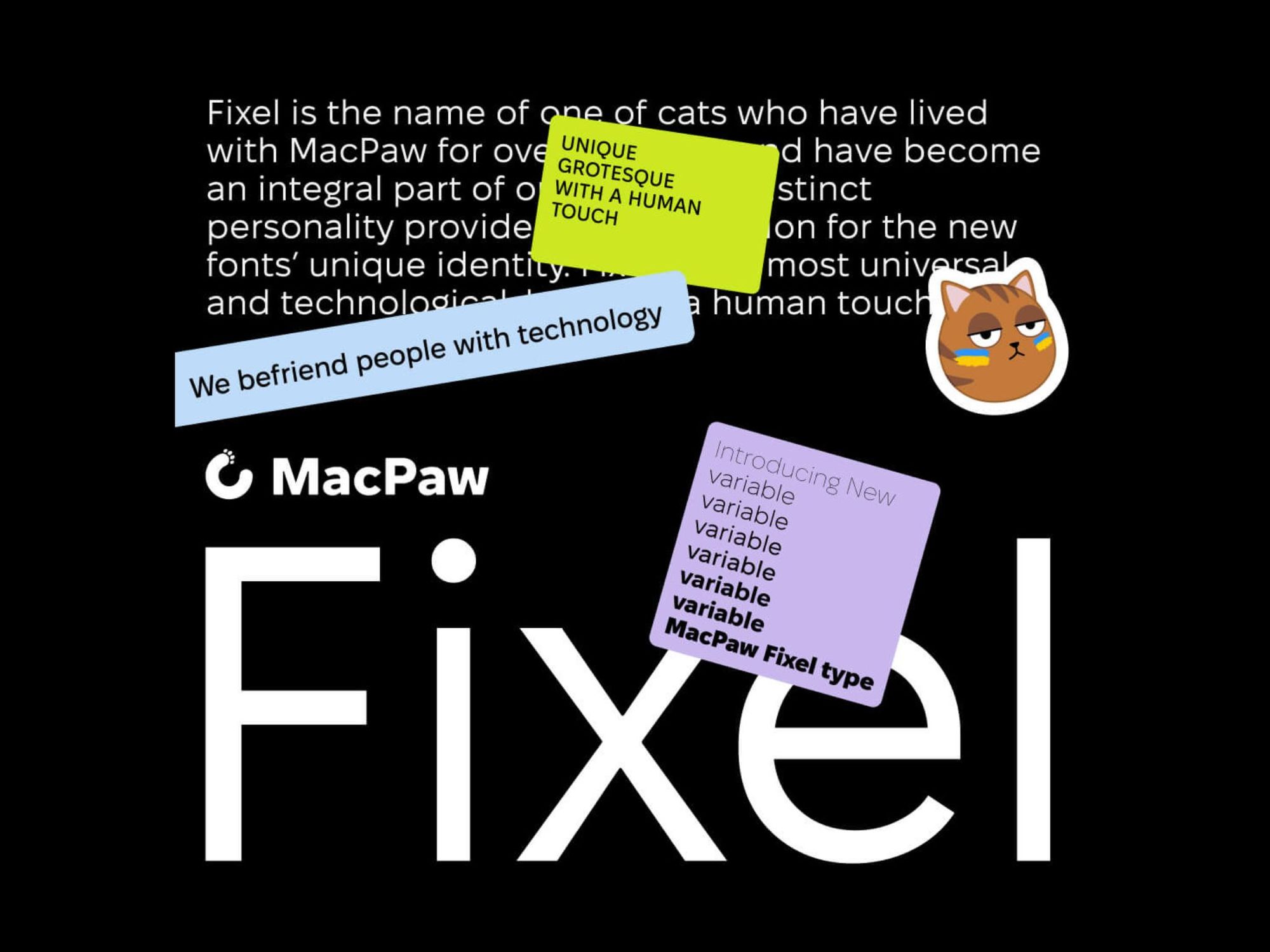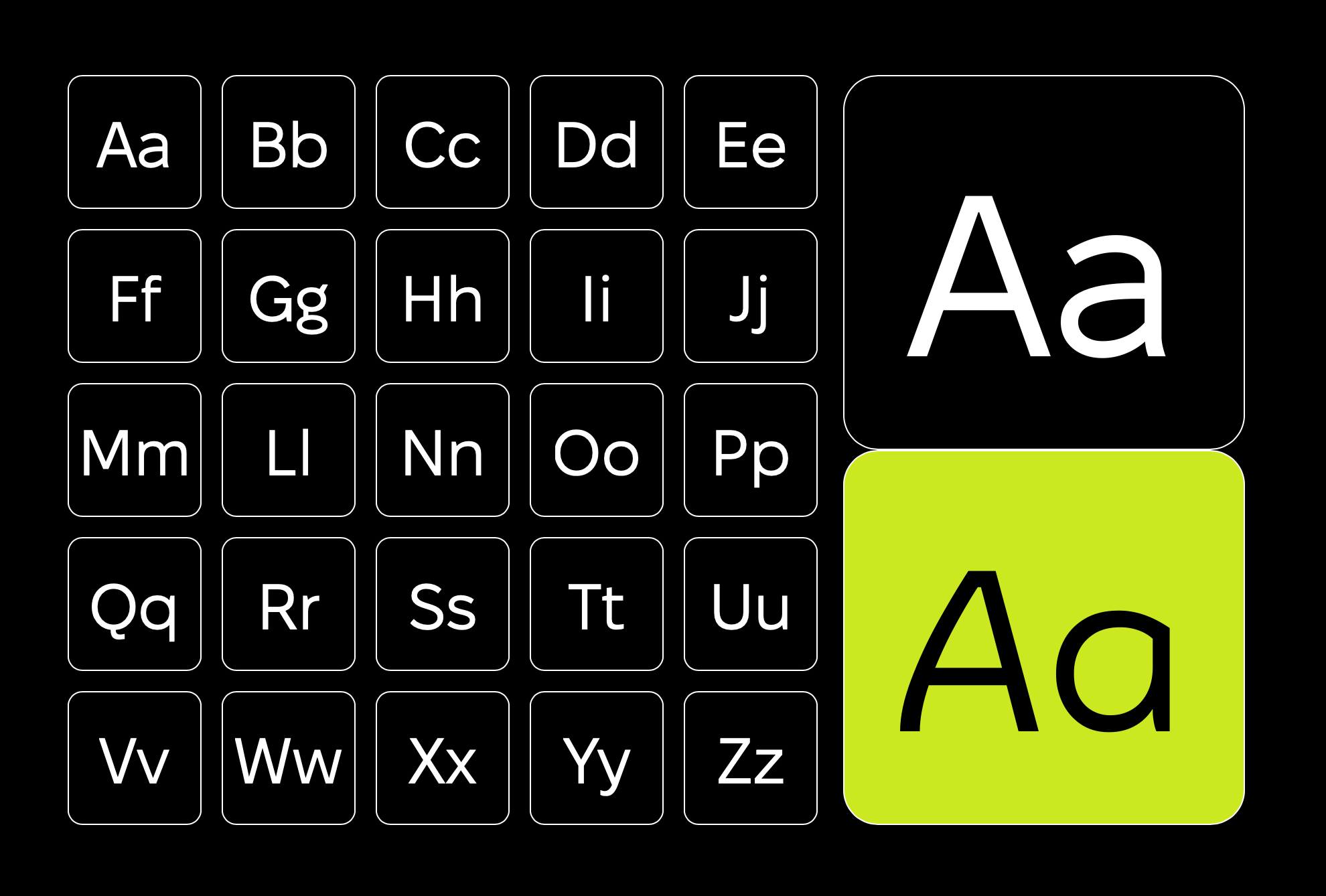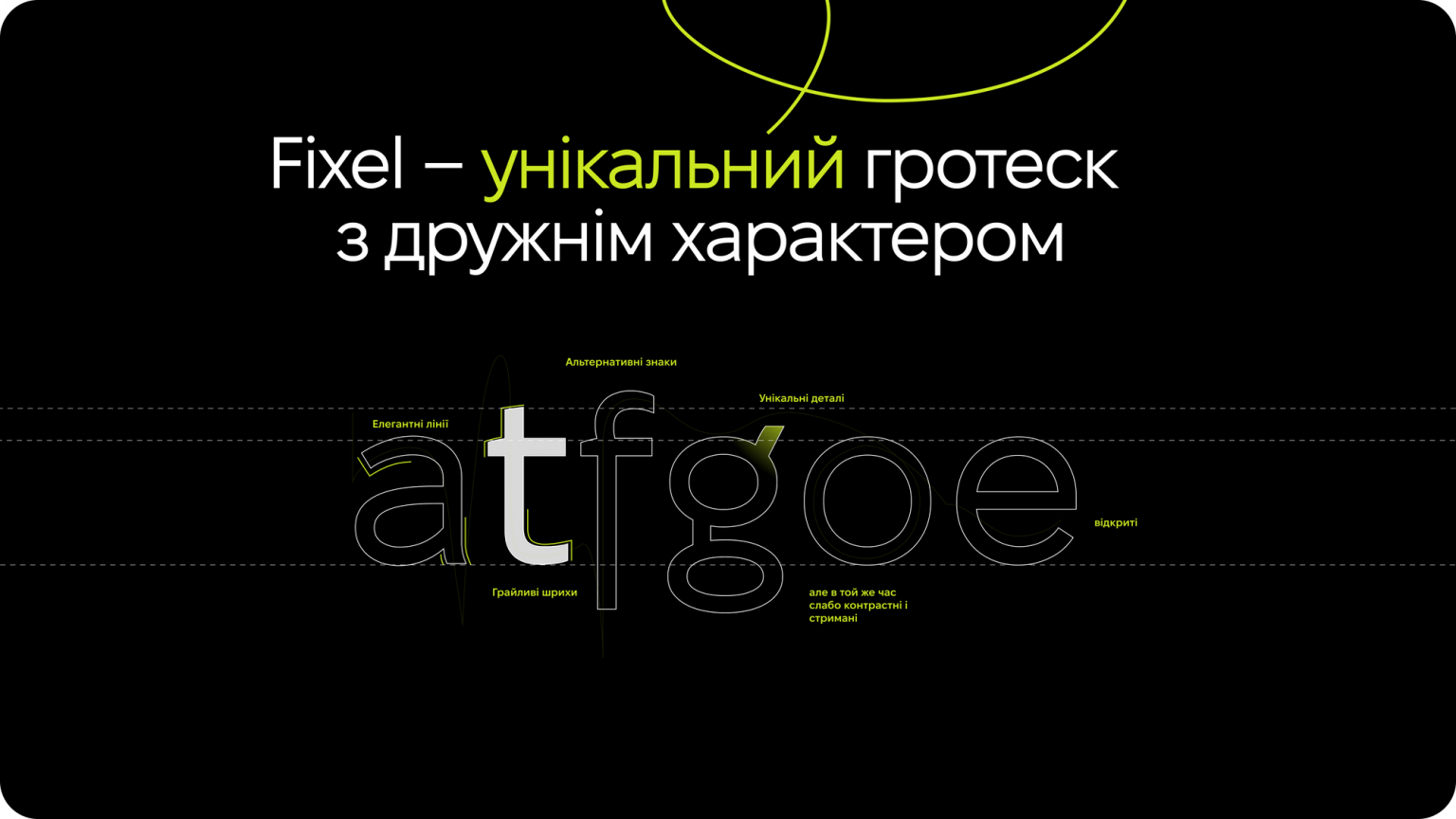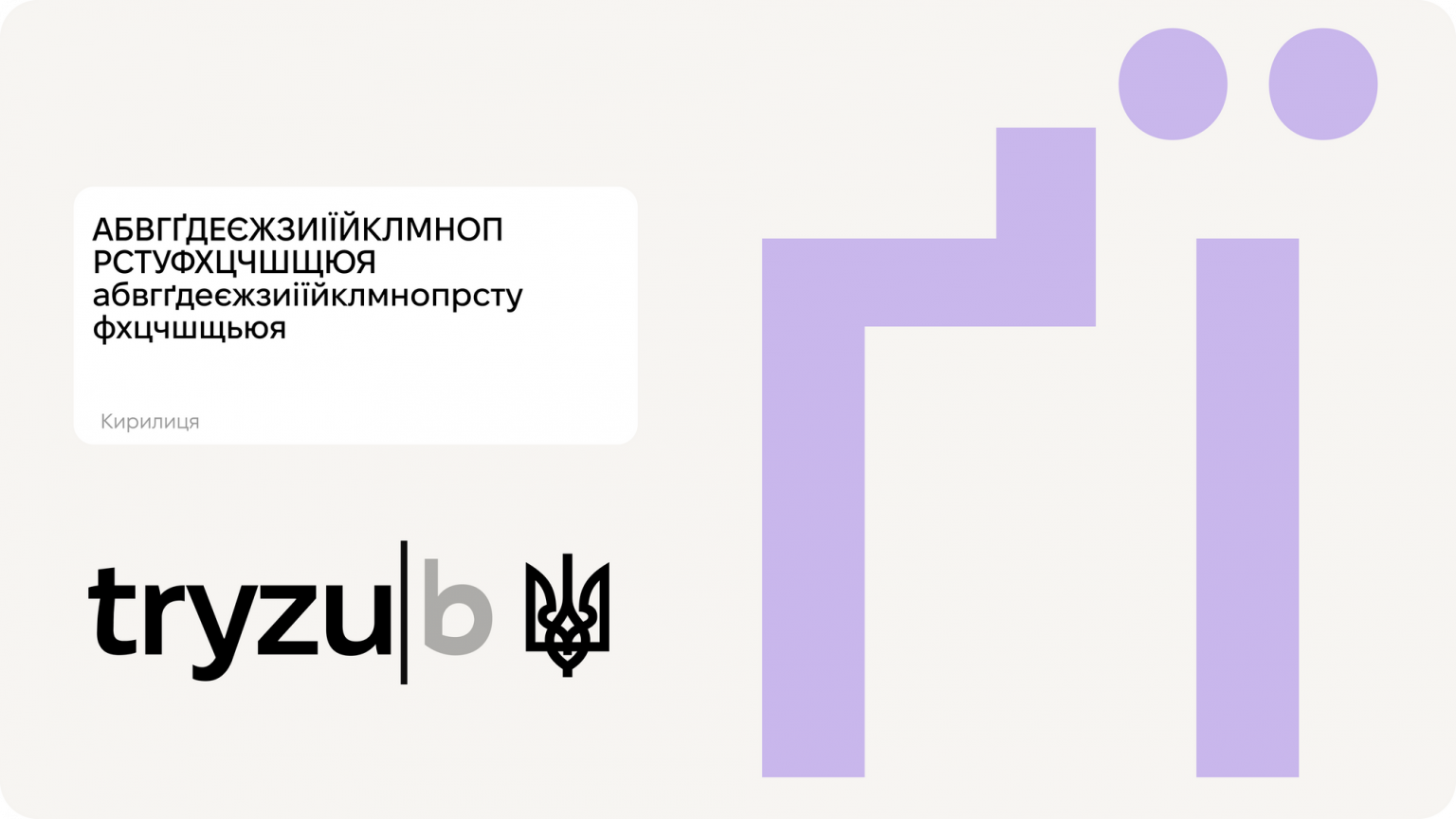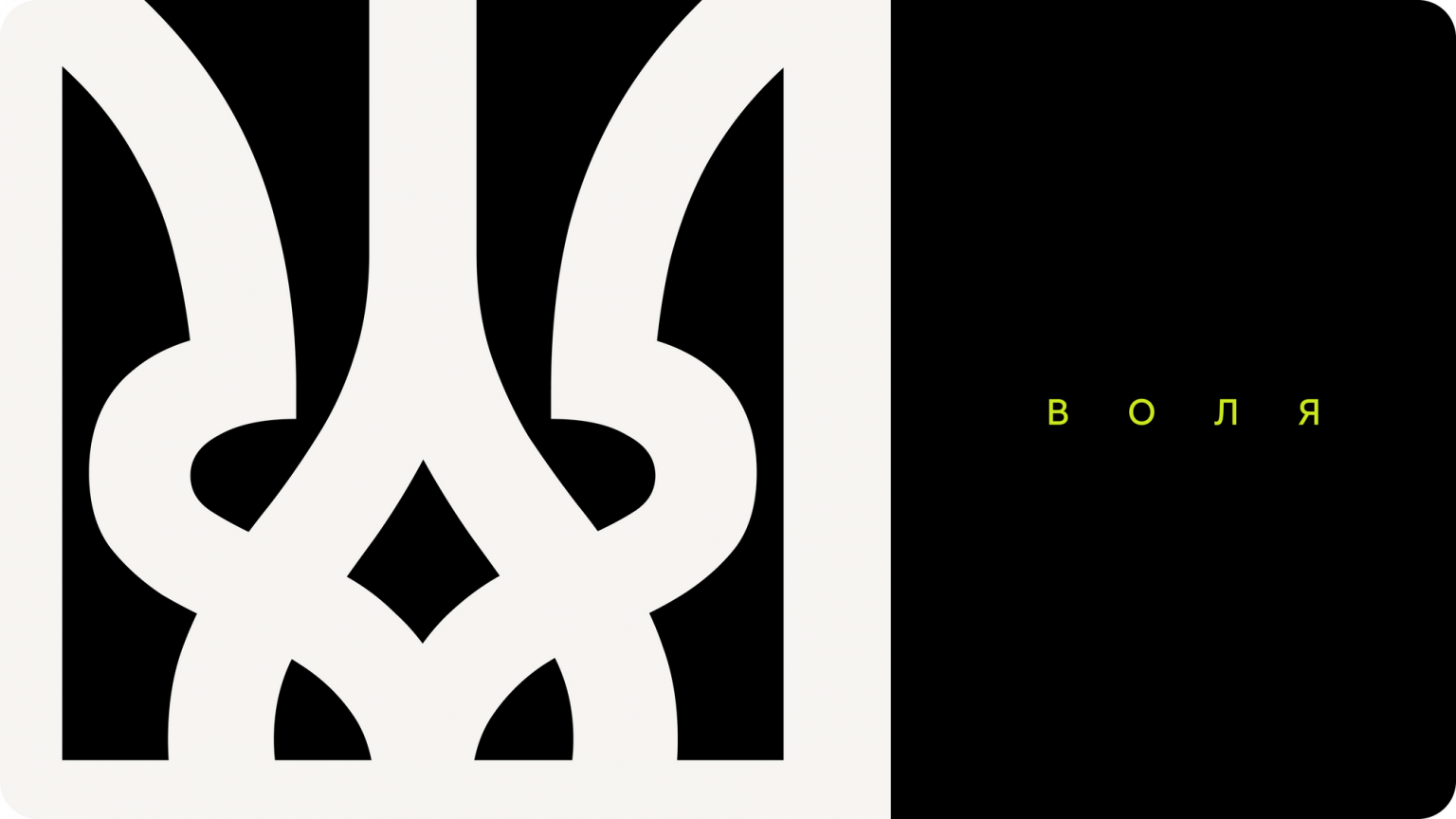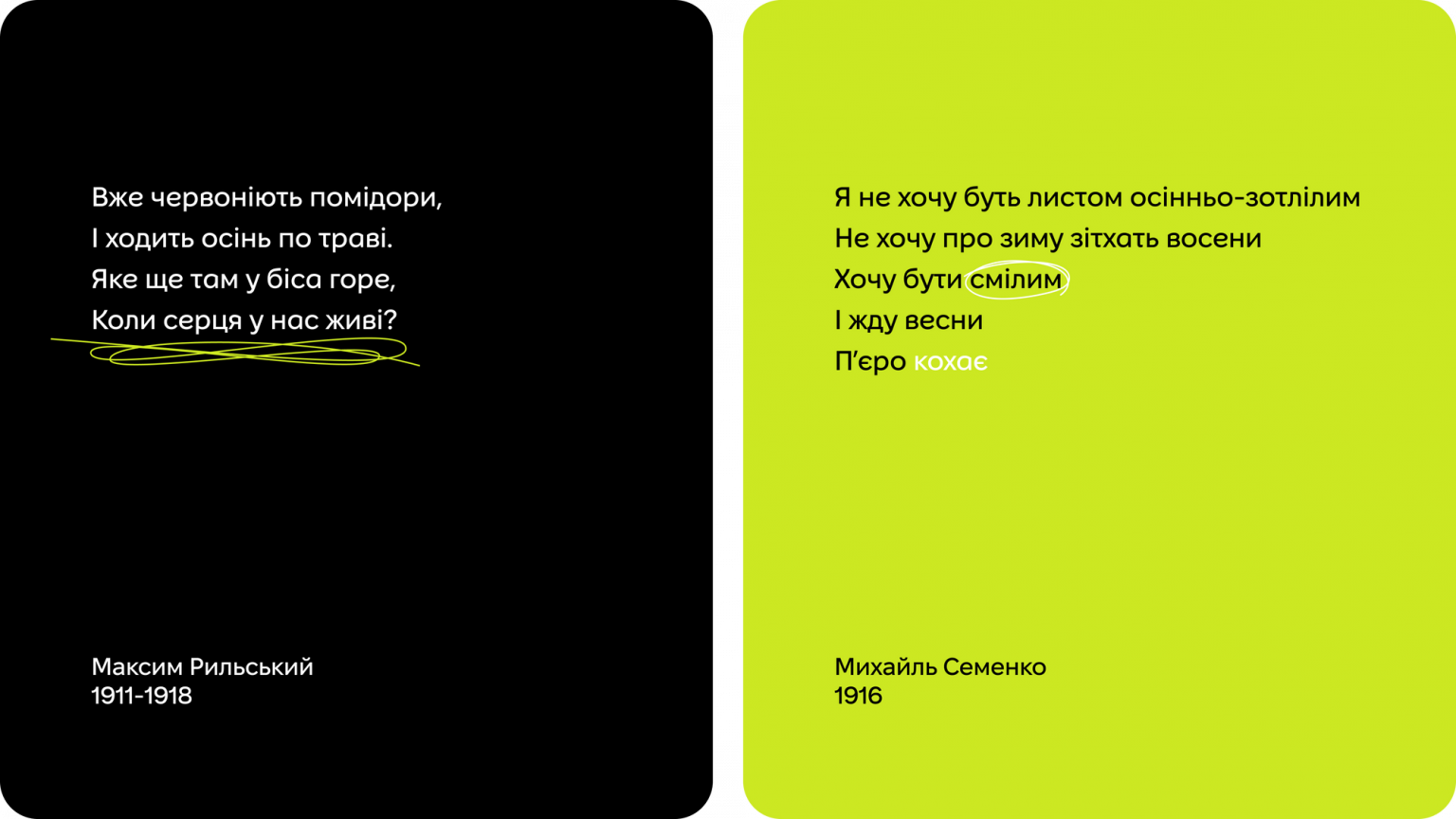
Fixel — безкоштовний український шрифт від MacPaw
Новий варіативний кириличний шрифт Fixel від української компанії MacPaw
У день української писемності та мови компанія MacPaw, компанія з розробки програмного забезпечення та інноваційних рішень для користувачів Mac, презентувала один із двох власних унікальних шрифтів — Fixel, який створили спільно з українською шрифтовою студією АльфаБраво.
Нові шрифти Fixel та Hoover назвали на честь улюбленців MacPaw — котів, які мешкають у просторі компанії й вже стали невіддільною частиною її команди та культури. Більш ніж десять років тому Віра Ткаченко, СTIO MacPaw, знайшла Фікселя у підвалі, коли він був ще малим кошеням. Хувер оселився в компанії пізніше, у 2014 році. Їхні характери й зовнішність стали натхненням для розробки особливостей і стилю шрифтів.
Про Fixel
Fixel — це новітній український шрифт у двох стилях, один для тексту, другий для дисплея. Шрифт пропонує дев’ять варіантів щільності, від тонкого до максимально товстого і чорного. Його відмінною рисою є унікальне поєднання геометричних і гуманістичних гротесків, результатом яких є відкриті форми літер, велика ширина, чіткі краї та низький контраст, що забезпечує баланс між стриманістю та відчуттям грайливості та динамічності.
Слід зазначити, що Fixel розроблено спеціально для використання на цифрових екранах, включаючи вебсайти, мобільні програми та цифрові вивіски. Шрифт також оптимізовано для чіткого, розбірливого читання, що робить його ідеальним вибором для сучасних дизайнерських проєктів.
Гарнітура має простий, сучасний, приємний для очей дизайн. Чисті лінії та чіткі краї полегшують читання та підтримують узгодженість типографіки навіть при невеликих розмірах літер та великих об’ємах тексту. Шрифт Fixel доступний у чотирьох вагах, включаючи звичайний, жирний, світлий і тонкий. Кожна вага має свою індивідуальність, що робить шрифт універсальним в залежності від проєкту та підібраної ваги.
Fixel від MacPaw має у своєму складі розширену латиницю та кирилицю, тому може «розмовляти» більш ніж 40 мовами, зокрема, рідною українською. Тож шрифт чудово підійде для проєктів з використанням різних мов та для роботи з міжнародними клієнтами. Окрім набору звичних форм літер та знаків, у шрифті Fixel присутні й альтернативні символи. Вони відрізняються від основних літер, оскільки є більш пластичними, мають посилену динаміку й асиметрію.
Історія створення Fixel
Раніше компанія MacPaw використовували виключно стандартні шрифти. Але у процесі ребрендингу компанія вирішила, що розробка власних шрифтів зможе не лише підкреслити особливості бренду, але й допоможе зробити комунікацію більш послідовною і впізнаваною. Технологічний Fixel та емоційний Hoover добре відображають цінності компанії й транслюють глобальну ціль MacPaw — to be friend people with technology. Власні шрифти також дозволять бути більш гнучкими та нададуть можливість змінювати комунікацію впродовж всієї трансформації компанії.
«Проєкт MacPaw Fonts почався з бажання покращити консистентність дизайну наших комунікацій. Ми почали шукати партнера, який зміг би разом з нами пройти цей захоплюючий шлях — створення повністю нового унікального шрифту компанії. Для нас було важливо отримати цей досвід разом зі спеціалістами з України. Ми обрали Кирила Ткачова та його студію АльфаБраво.»
«Пишаємося тим, що нові шрифти Fixel та Hoover — результат роботи українських дизайнерів, що вкотре показує, які талановиті люди живуть поруч з нами, і коли ми працюємо разом — обов’язково досягаємо своїх цілей», — розповідає Олександр Агєєв, Chief Design Officer MacPaw.
Важливим аспектом є те, що MacPaw має українське коріння, що чітко відображено новітньому Fixel, де серед альтернативних символів є наш український тризуб, дизайн якого розробив український художник Ніл Хасевич ще у 1949 році. Версія тризуба залишили такою ж стильною, сучасною, зберігаючи свою народну автентичність. У MacPaw та АльфаБраво сподіваються, що Fixel допоможе зберегти та популяризувати спадщину видатного українського художника, а також підкреслить українське походження шрифту.